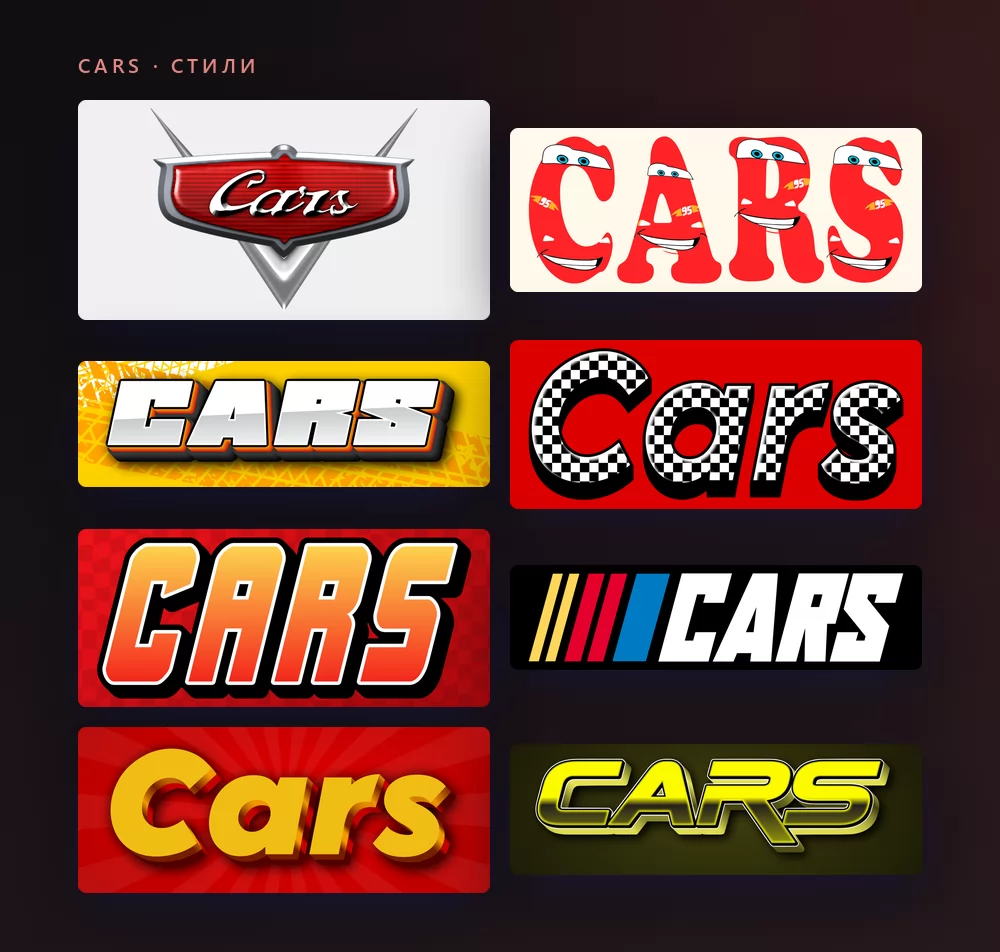
О шрифте «Тачек»
«Тачки» это фильм Pixar 2006 года, комедия в мире, где персонажи это автомобили. Его название не набрано, оно построено: хромированная надпись, вставленная в геральдический щит, ближе к украшению на капоте седана пятидесятых, чем к киноплакату.
Сам леттеринг очень близок к Magneto Bold, нарисованному Лесли Кабаргой и выпущенному Font Bureau в 1995 году. Собственная типографическая страница Microsoft описывает его как напоминание о «надписях из хромированных накладок на округлых формах дверец холодильников и багажников автомобилей сороковых и пятидесятых», то есть ровно о той эпохе, которую цитирует фильм.
Как сделать текст в стиле «Тачек»
Шаг 1. Введите имя
Откройте генератор и замените пример своим текстом. Эмблема строится вокруг слова, так что она сделана именно для имени: щит заполняется прямо во время набора.
Шаг 2. Выберите стиль
Стиль на целевой странице это эмблема: хромированная надпись, красная эмаль, серебряный щит. В списке есть и вся гоночная сторона фильма: клетчатые флаги, следы шин, гоночные полосы и буквы с глазами Молнии Маккуина. На вкладке «Стиль» в обоих случаях меняются заливка, контур и тень.
Шаг 3. Выберите формат
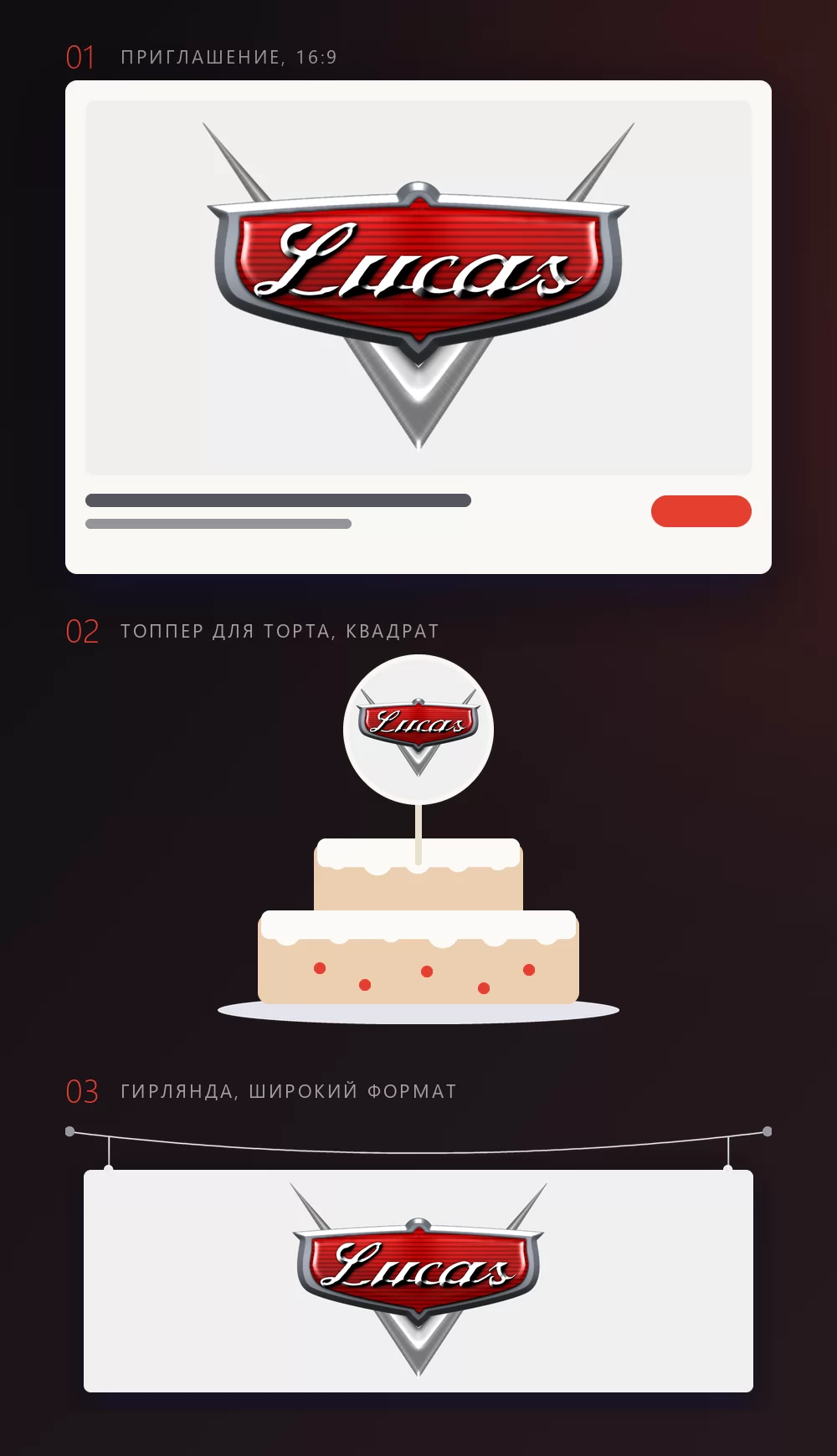
Задайте формат до экспорта, и потом ничего не придётся обрезать. 16:9 для приглашения, квадрат для топпера или аватарки, широкая полоса для гирлянды над столом. Три макета выше показывают, во что превращаются эти форматы, когда оказываются на своём месте.
Шаг 4. Скачайте
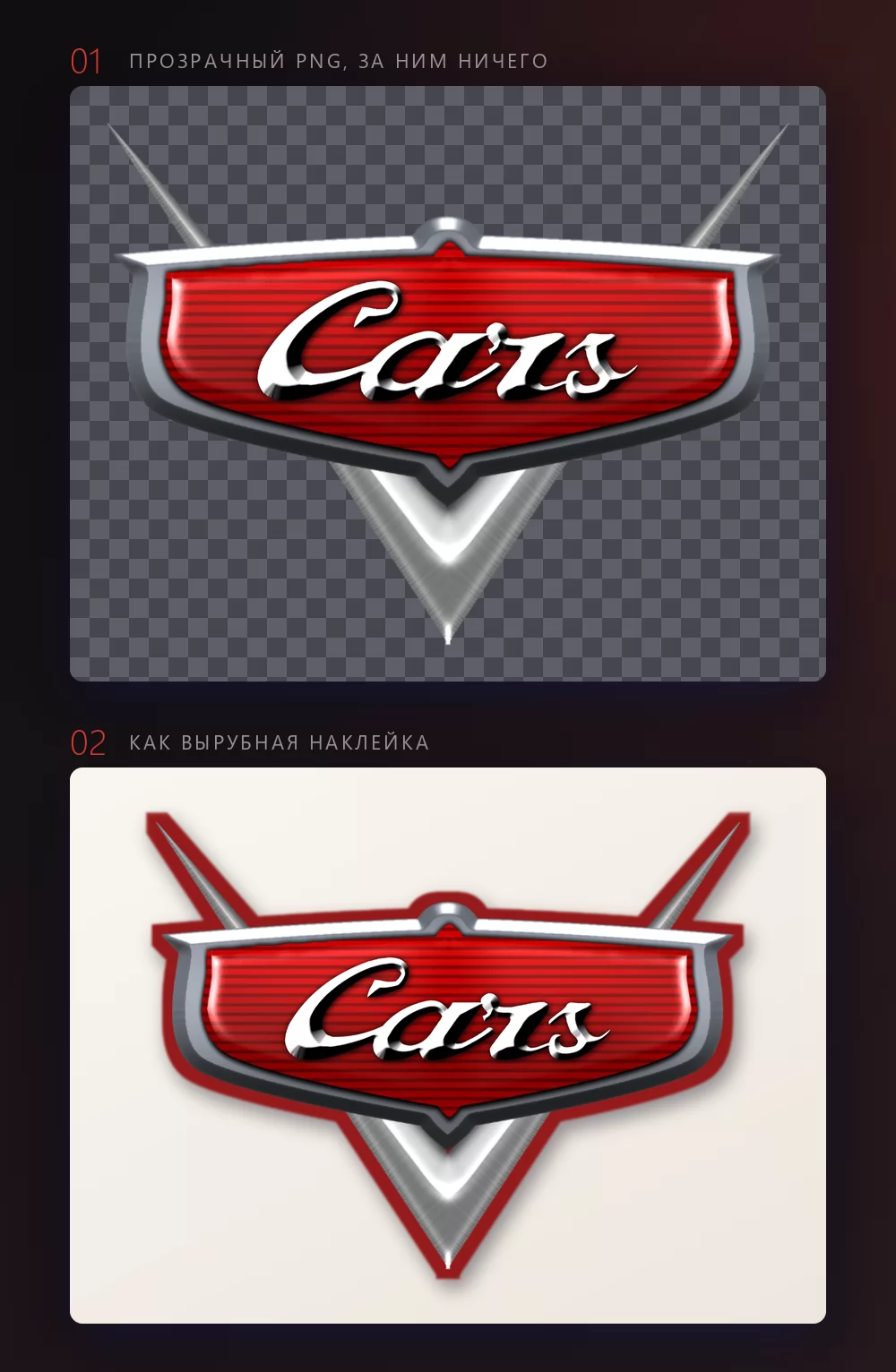
Сколько букв помещается в щит
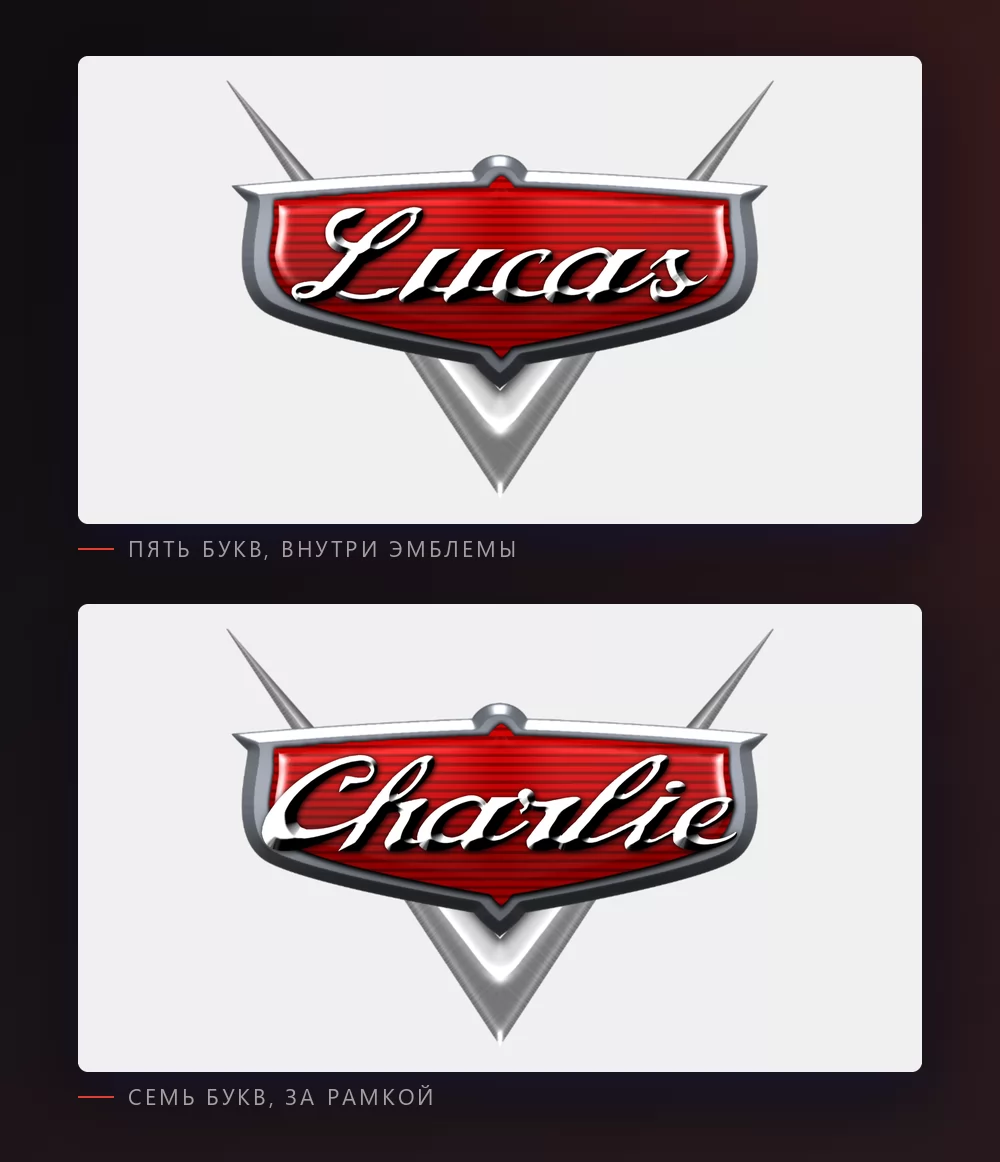
Мы это измерили, потому что от этого зависит выбор стиля. Щит свободно вмещает пять букв. На шести первая и последняя касаются серебряной кромки. На семи они уже снаружи, как выше.
И в отличие от всех остальных стилей, уменьшить текст не помогает: эмблема растёт вместе со словом, так что пропорция не меняется. Для длинного имени ответ это не настройка, а другой стиль. Гоночные заглавные из того же списка принимают любую длину, у них нет рамки, из которой можно выпасть.
Эмблема или буквы Маккуина
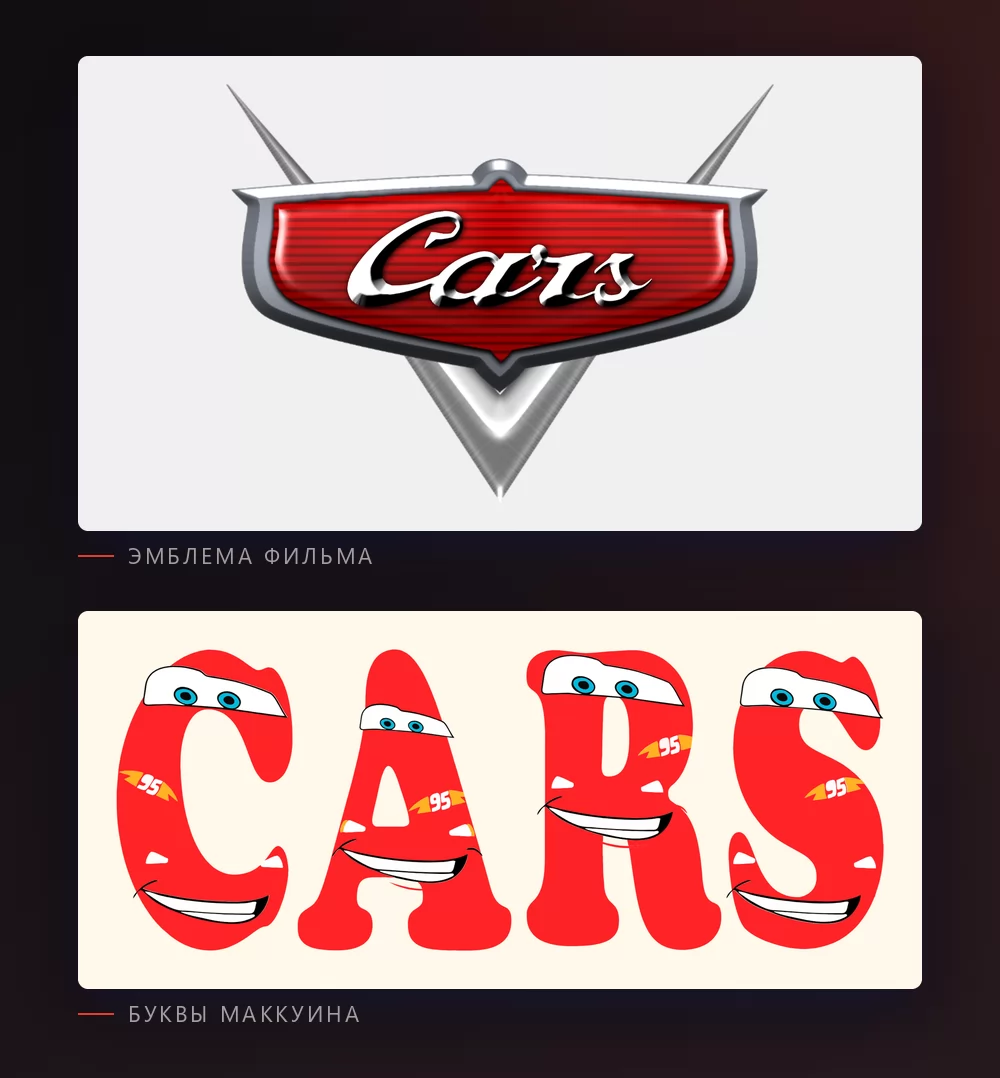
Эмблема это форма логотипа фильма: хромированная надпись на красной эмали внутри серебряного щита. Именно её представляют, когда говорят «логотип Тачек», и именно она подходит для имени на приглашении.
Буквы Маккуина это вторая половина того, что ищут: каждая буква это маленькая красная машина, с глазами в лобовом стекле и молнией 95 на боку. Они говорят о персонаже, а не о фильме, и работают лучше на гирлянде, чем сжатыми в аватарку.
Оба стиля в одном списке: можно попробовать имя в одном, потом в другом, не уходя со страницы.
Какой шрифт ставить, если он всё-таки нужен
Magneto Bold это опознанный шрифт, и первое место, где его стоит искать, это ваш собственный компьютер: он идёт с Microsoft Office. Откройте меню шрифтов в Word и наберите название. Если он там, дело сделано, и вы ничего не купили.
Если его там нет, Magneto продаётся у Font Bureau и его дистрибьюторов. Это настоящая коммерческая лицензия, поэтому копии, гуляющие по сайтам бесплатных шрифтов, нелегитимны.
Для открытой лицензии честный выбор это Alfa Slab One на Google Fonts, нарисованный JM Solé в 2012 году под SIL Open Font License. Понимайте, что он даёт, а что нет: это египетский шрифт, он приносит вес и уверенность, но не росчерк. Именно его молча используют несколько других генераторов.
Ни один из них не даёт вам щит. Эмблема это форма, а не шрифт, поэтому генератор рисует её вокруг вашего текста, вместо того чтобы отправлять вас на поиски.
Для чего это используют на самом деле
Дни рождения в первую очередь и с большим отрывом: приглашение, гирлянда над столом, топпер для торта, имя на двери комнаты, номер на самодельной трассе. Дальше таблички на дверь в классе, превью на YouTube для видео про машинки и иногда футболка к семейному празднику. Почти всё это получается лучше с прозрачным PNG, чем с установленным шрифтом, потому что узнают щит и хром, а файл шрифта даёт только форму букв.
Как сделать текст «Тачек» в Canva
Как сделать гирлянду ко дню рождения в стиле «Тачек»? Введите имя, выберите широкий формат, скачайте прозрачный PNG и напечатайте на цветной бумаге, которую используете.